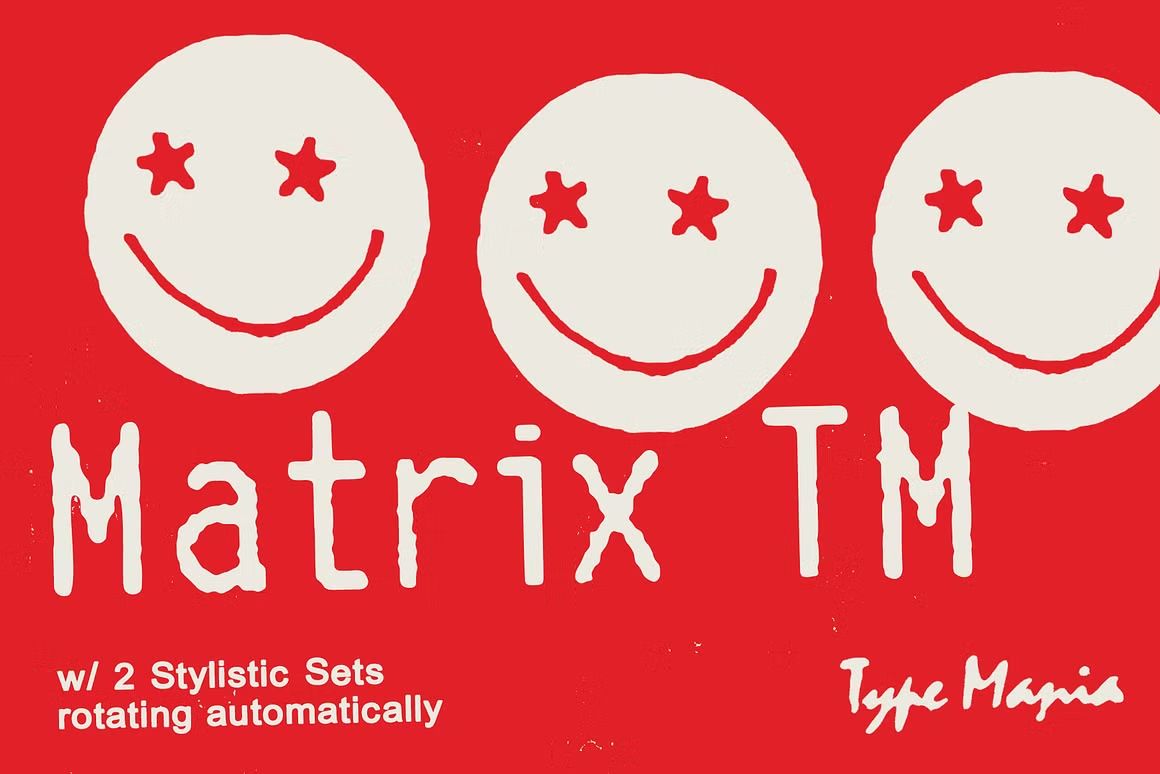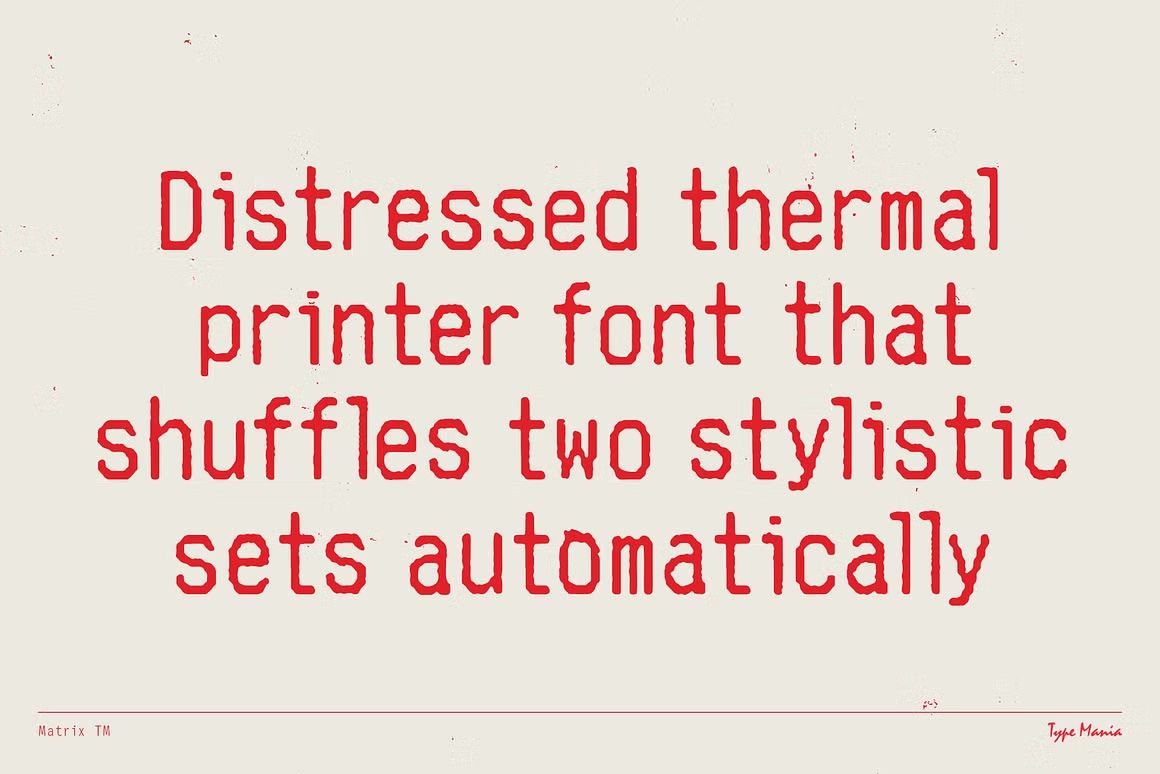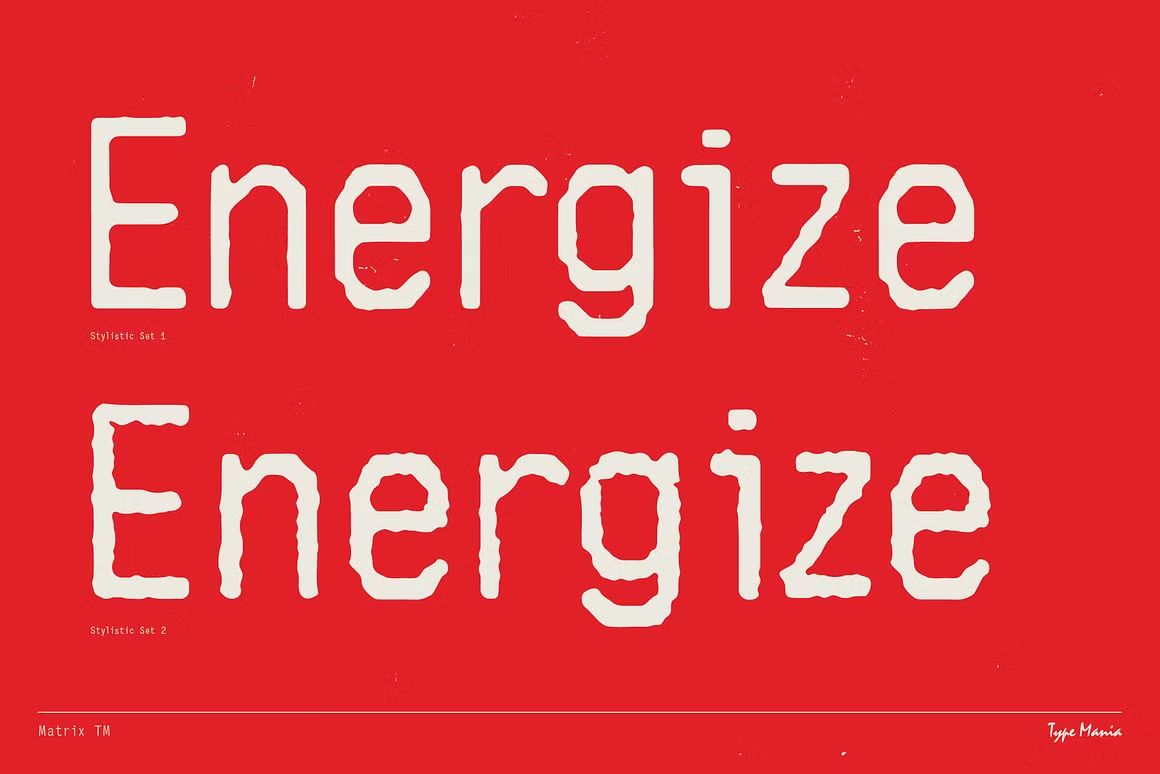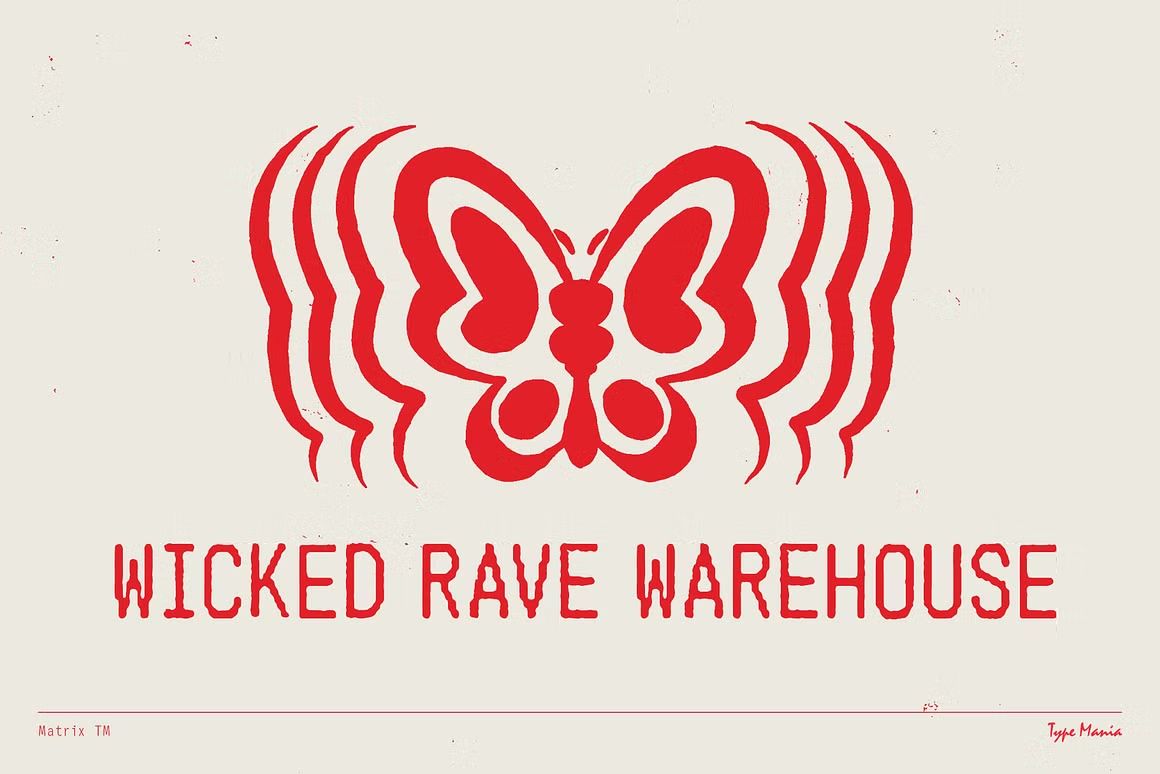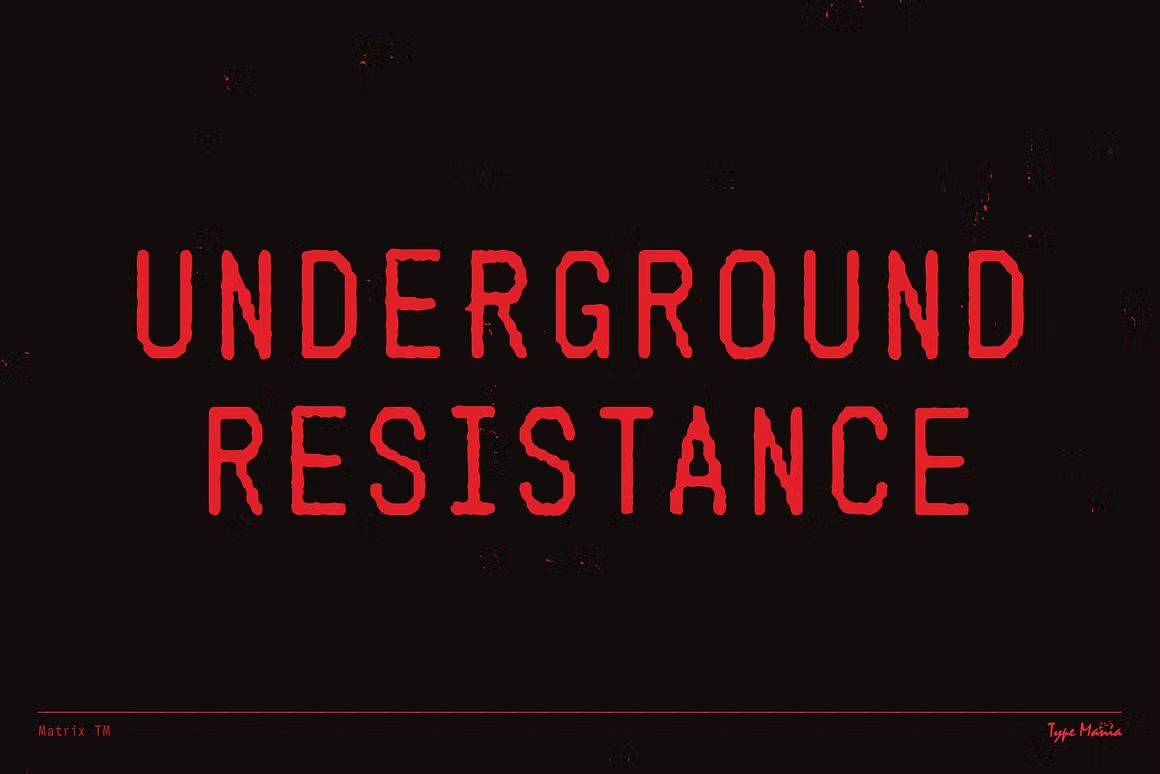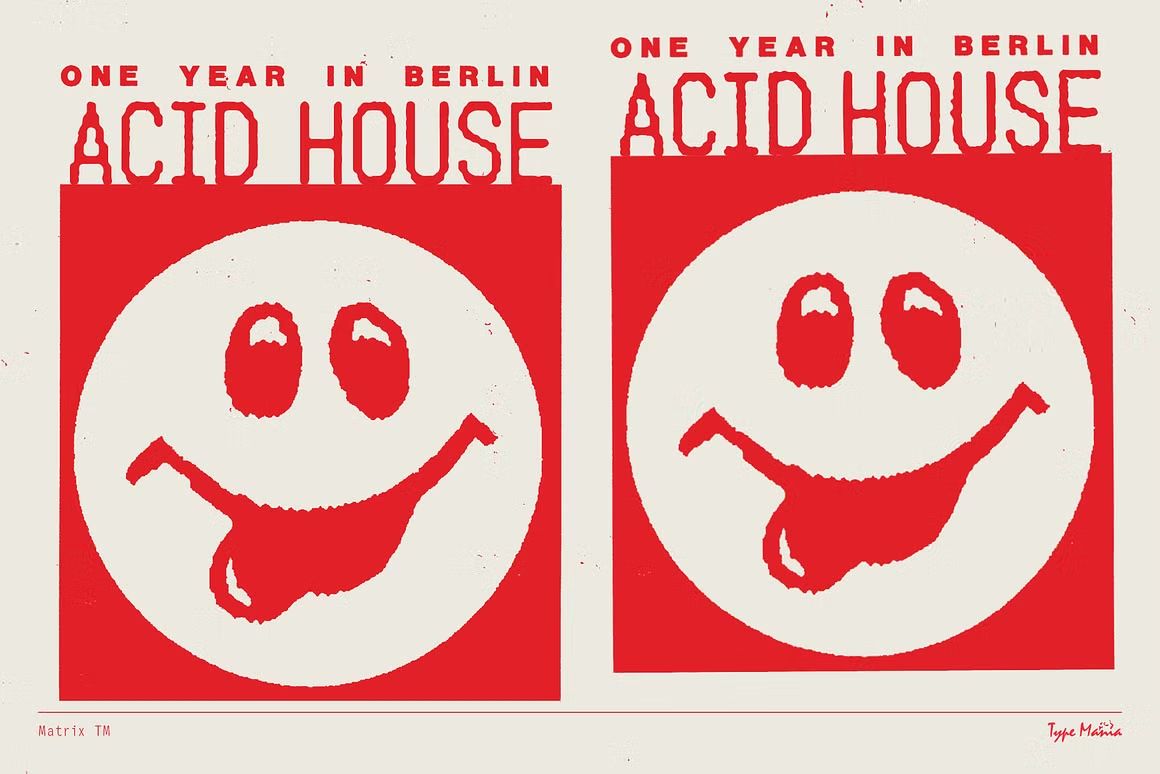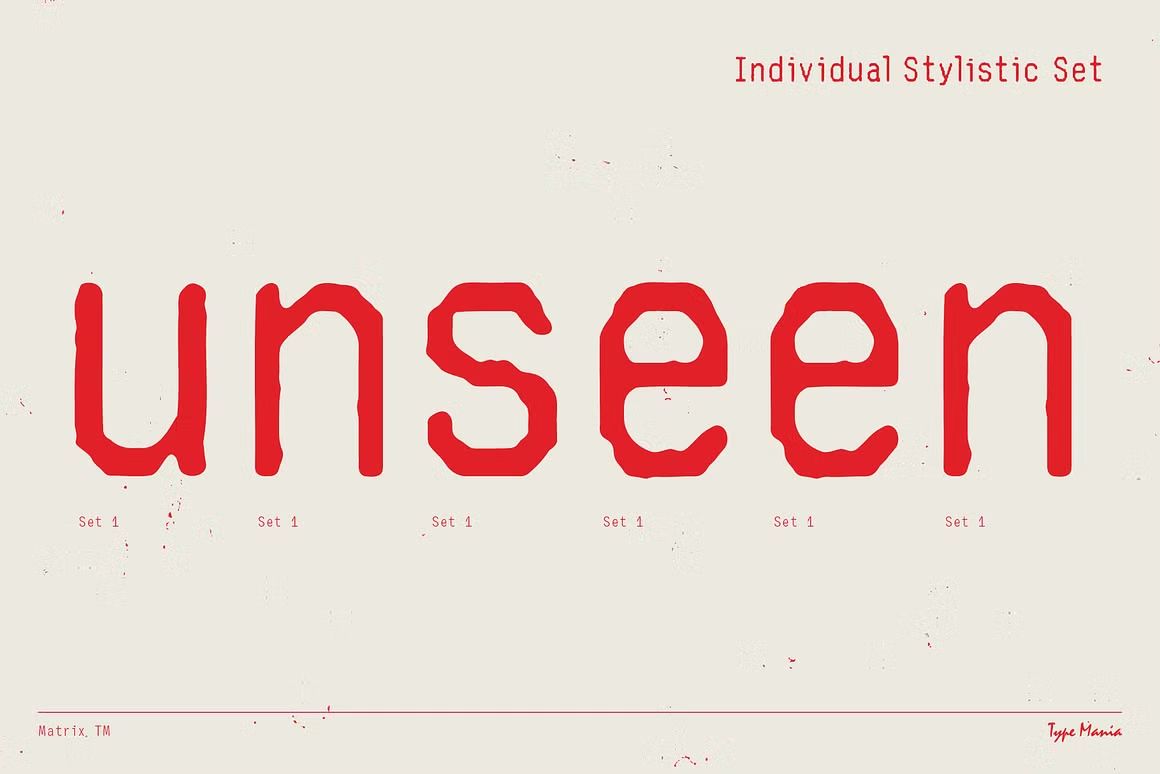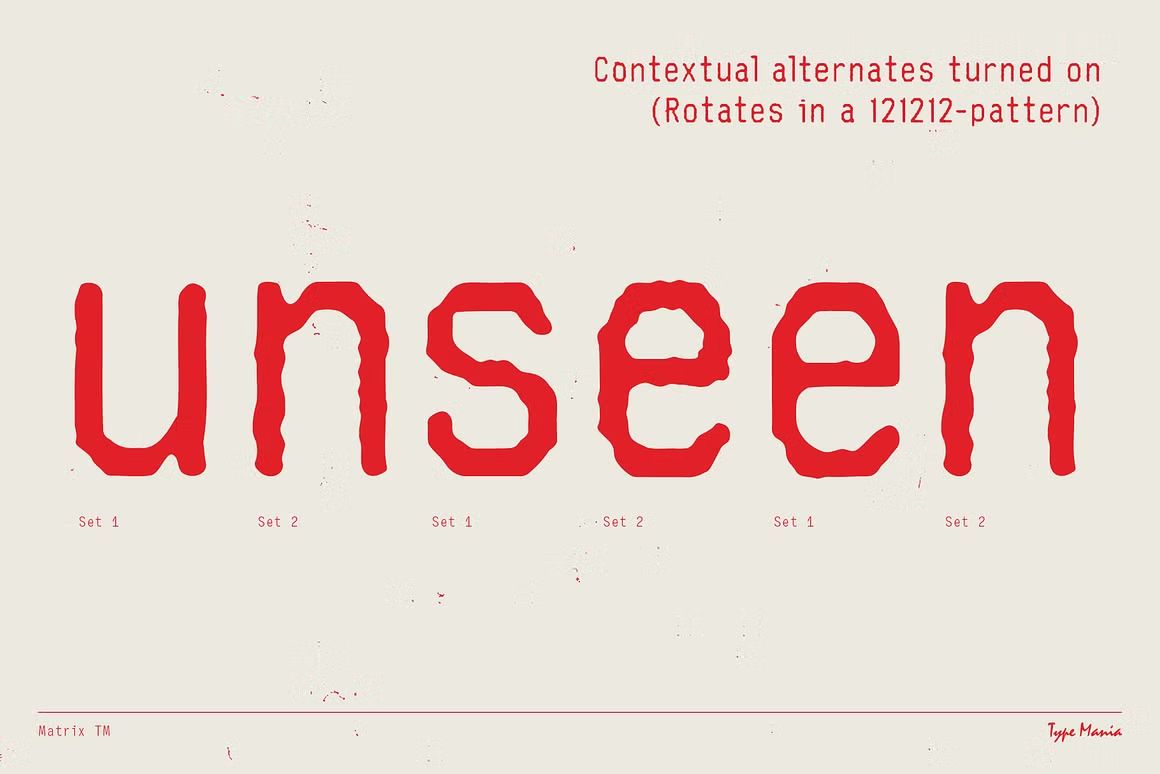
Matrix TM – Sans Serif Font
Matrix TM adalah font sans serif futuristik dan tegas, cocok untuk branding teknologi dan desain modern. Format OTF/TTF/WOFF, siap digunakan.
Matrix TM adalah font sans serif modern dengan gaya futuristik dan tegas. Menampilkan bentuk huruf geometris, bersih, dan minimalis, font ini cocok untuk branding teknologi, UI/UX, poster, kemasan, dan desain digital yang membutuhkan tampilan modern dan canggih. Matrix TM menghadirkan kesan profesional, kuat, dan inovatif dalam setiap penggunaannya.
• Sans serif geometris dengan gaya futuristik
• Ideal untuk teknologi, startup, dan desain digital modern
• Termasuk huruf kapital, kecil, angka, dan simbol